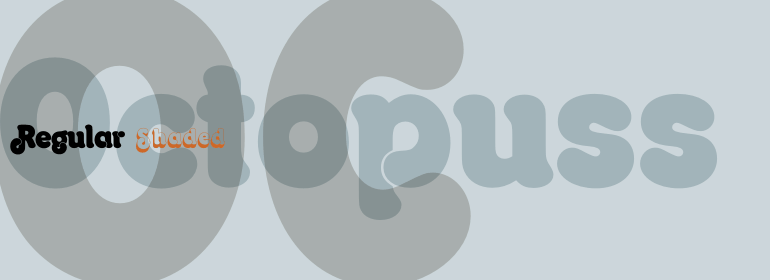
Octopuss™
Octopuss™,这款字体结构工整、笔画清晰,兼顾美观与易读性,适用于标题、正文、海报、包装、LOGO 等多种场景。字形优雅稳定,风格百搭耐看,适配日常排版与创意设计,让文字呈现更舒适、更具质感。Octopuss™一笔一画,皆是细节,以均衡的比例、流畅的线条打造舒适视觉体验,字形端正大气,风格简约现代。无论是商业设计、品牌宣传还是日常排版,都能轻松驾驭,让文字更有格调与力量。Octopuss™字体下载。
Octopuss是由Colin Brignall于1970年为Letraset干式转印纸设计的一款充满活力的烫金字体(titling typeface)。Brignall用带有阴影的轮廓变化增强了基本字母表,从而使该字体有种三维的效果,就好像是在浮动一样。Octopuss字体清晰无误地展示了20世纪70年代的字体风格,同样有Brignall设计的Countign和Harlow也是如此。大写字母基线以下的圆形笔画非常引入注目而且独具特色。由于小写字母的白色空间很小,圆形、粗壮的Octopuss只能用作标题字体,且应设置为大字号。
Octopuss is an energetic titling typeface designed in 1970 by Colin Brignall for Letraset dry transfer sheets. Brignall expanded the basic alphabet with an outline variation with a shadow, which makes the typeface look three dimensional, almost like it is floating. Octopuss font displays the unmistakable signs of the typefaces of the 1970s, as do Countdown and Harlow, also designed by Brignall. The circular strokes of the capitals that drop well under the base line are striking and unique. Because of the small white spaces of its lower case letters, the rounded, robust Octopuss is meant exclusively as a headline font and should be set in large point sizes.